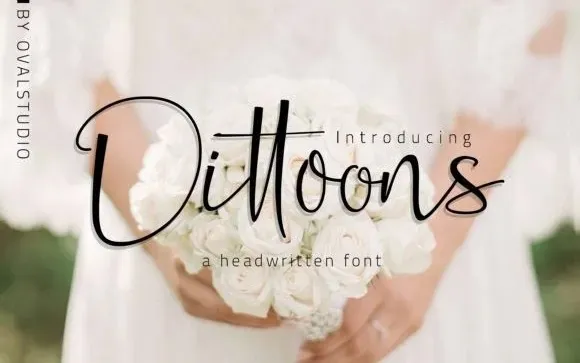
Dittoons Font – Fonte Grátis
Dittoons Font
A ‘Dittoons Font’ é uma atraente fonte script criada para designers que desejam dar um toque elegante aos seus projetos gráficos. Seu aspecto delicado e artesanal transmite sofisticação, oferecendo uma visão fresca e encantadora para qualquer projeto. Esta font foi especialmente projetada para fornecer um visual agradável em variedades de aplicativos, como convites de casamento, cartas de agradecimento, cartões da Mãe, frases de incentivo, cartões de boas-vindas, logotipos, camisetas personalizadas e até mesmo para cards comerciais. Seu uso é sinônimo de estilo e refinamento em qualquer situação de design.